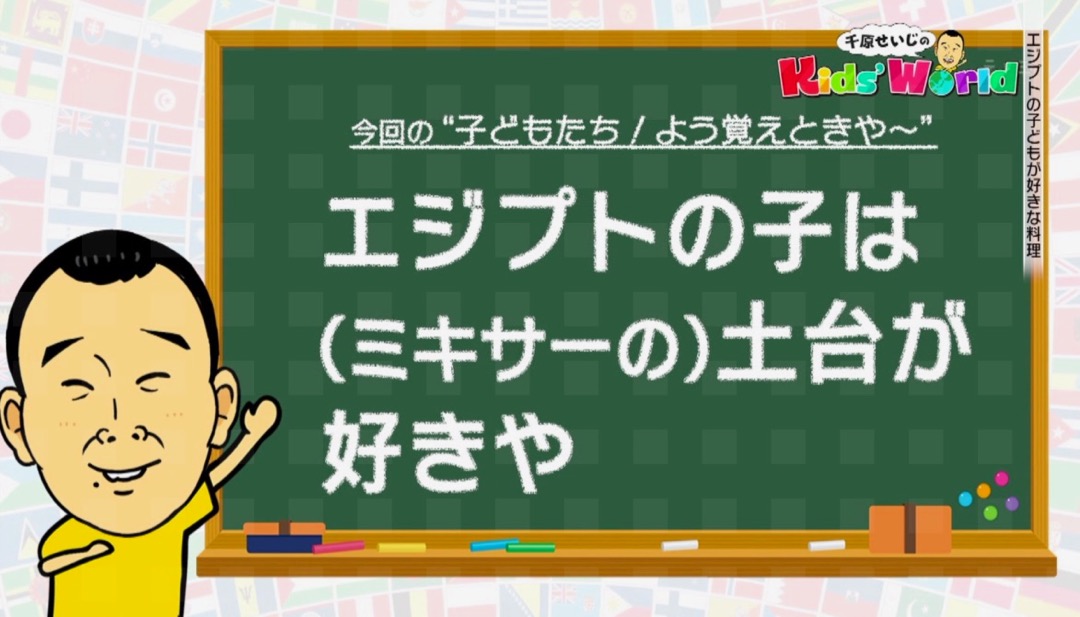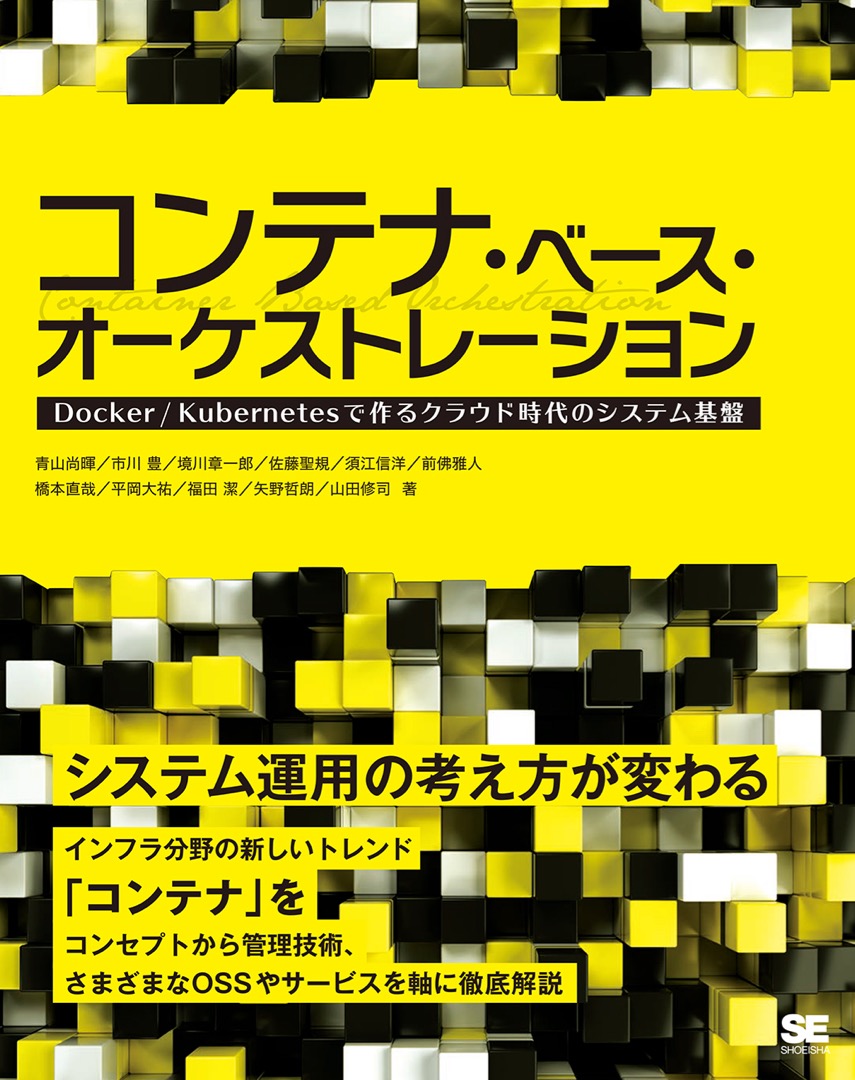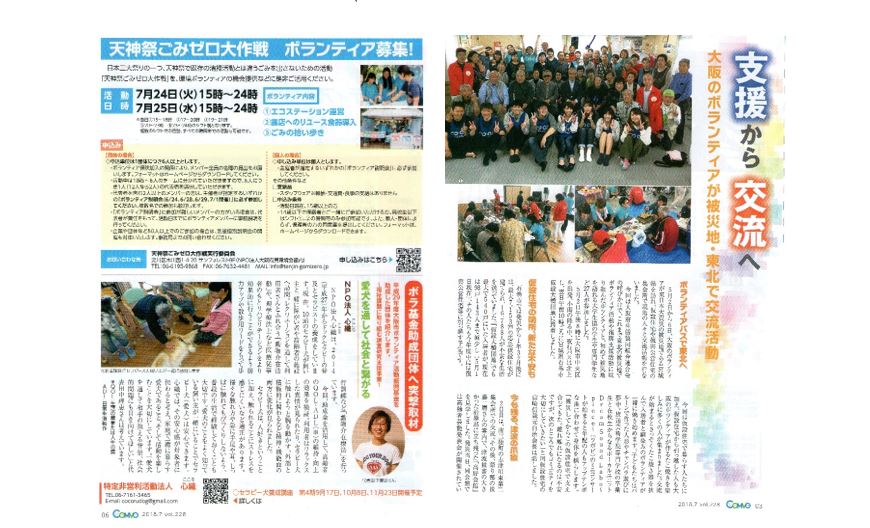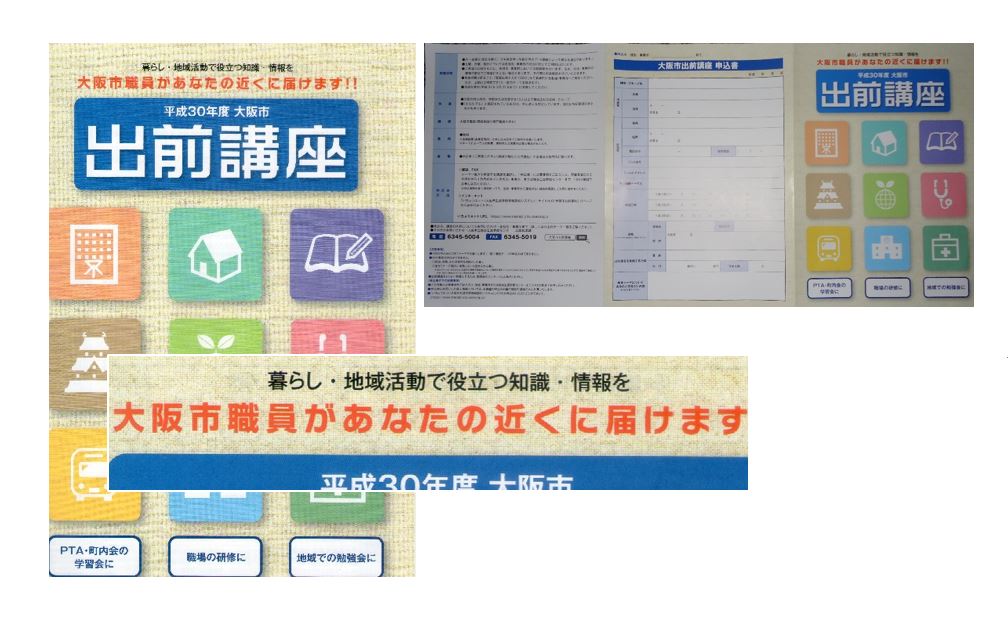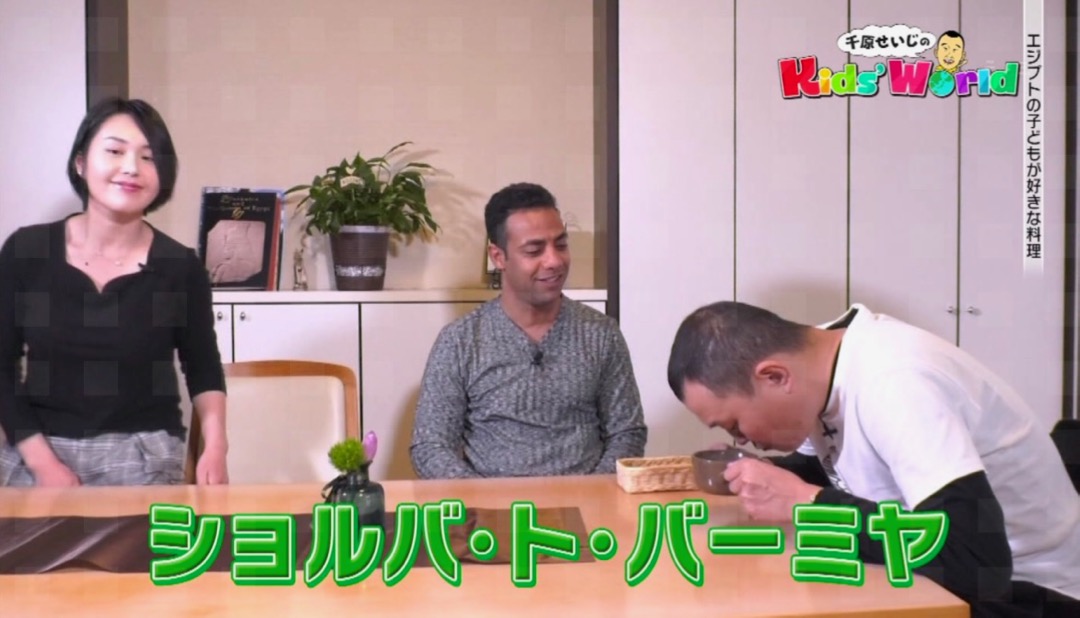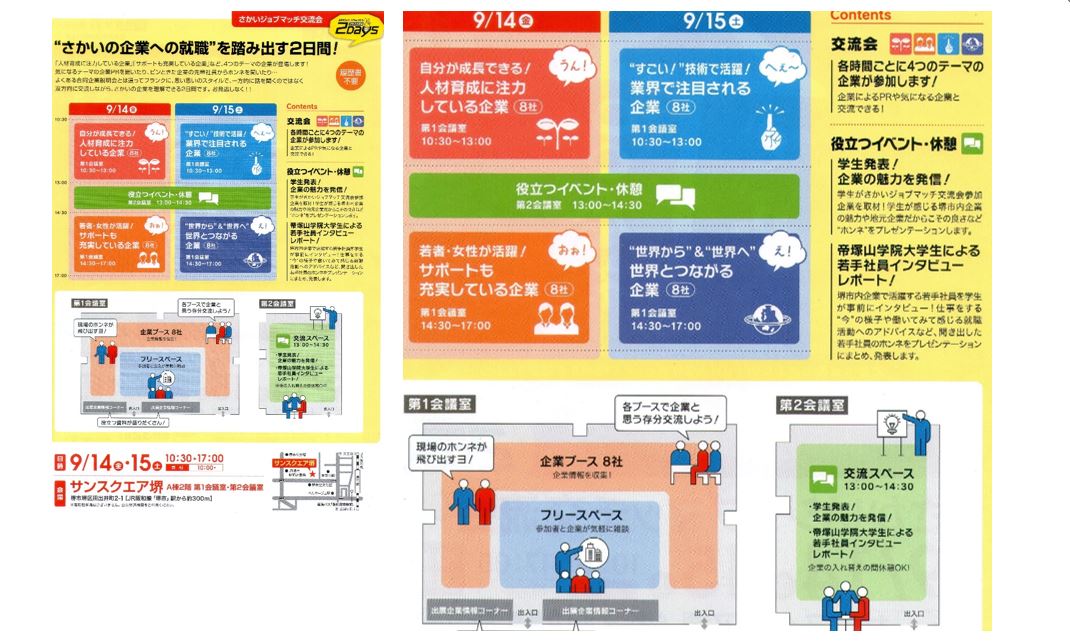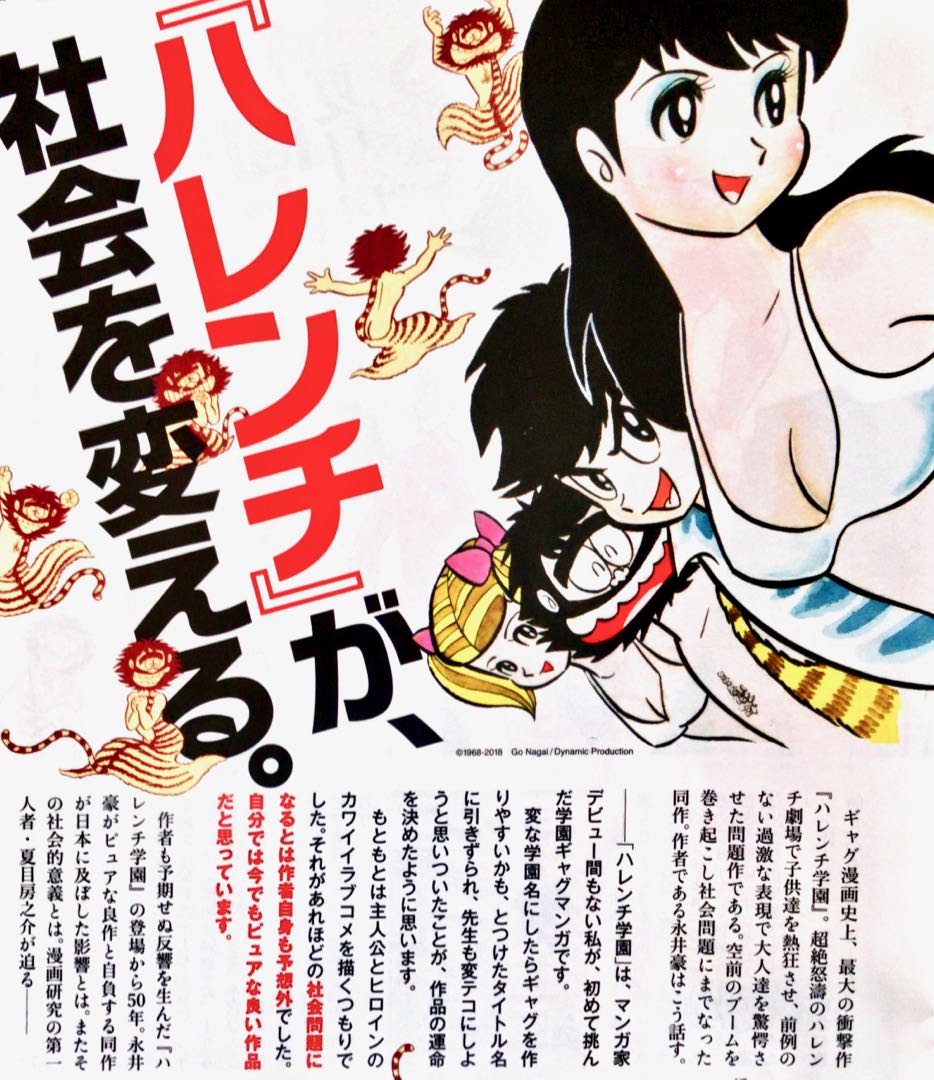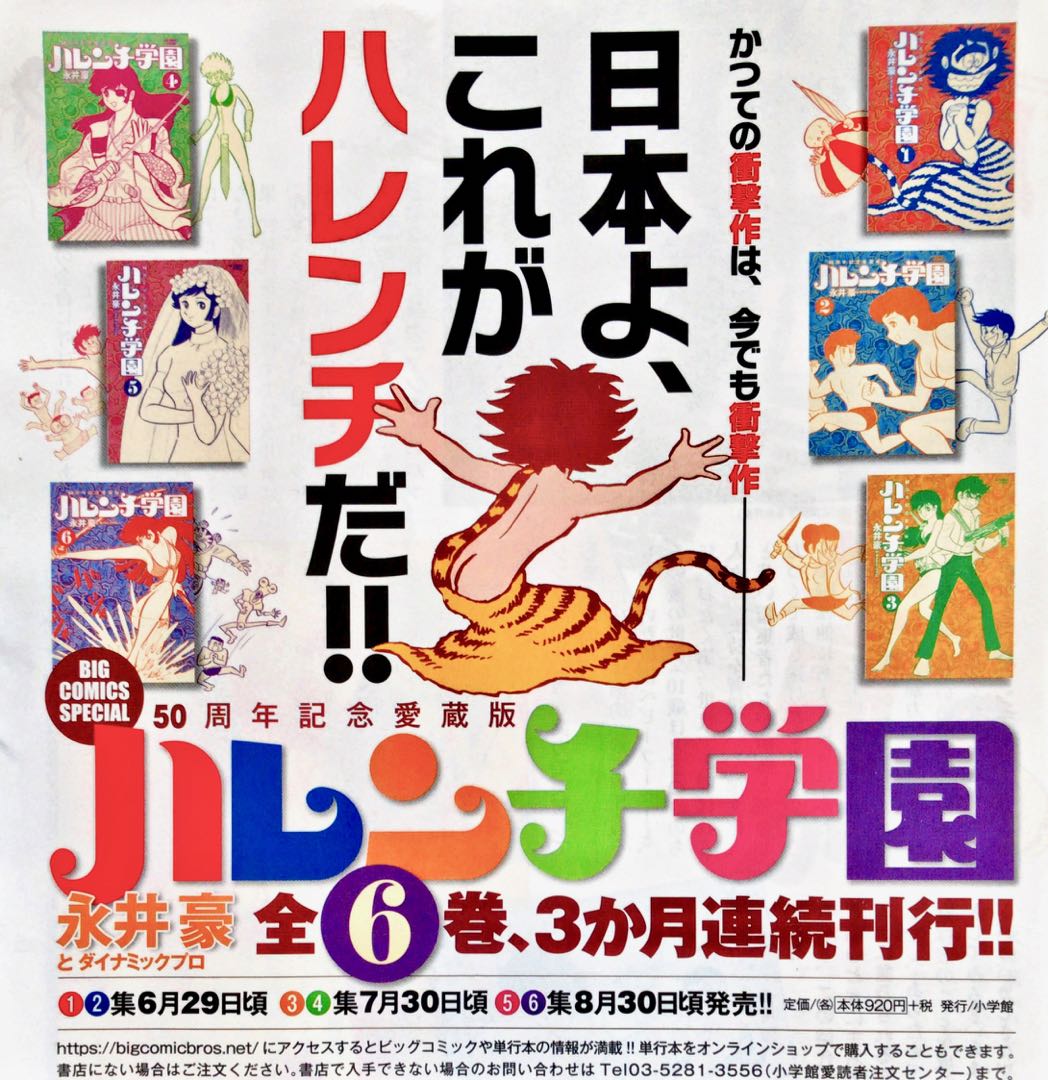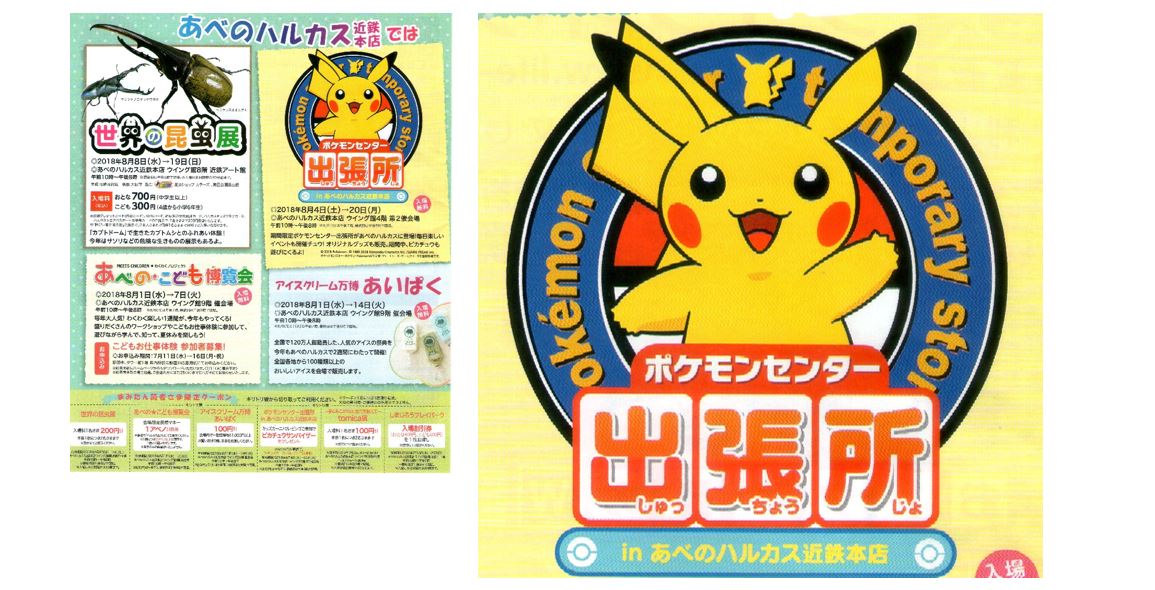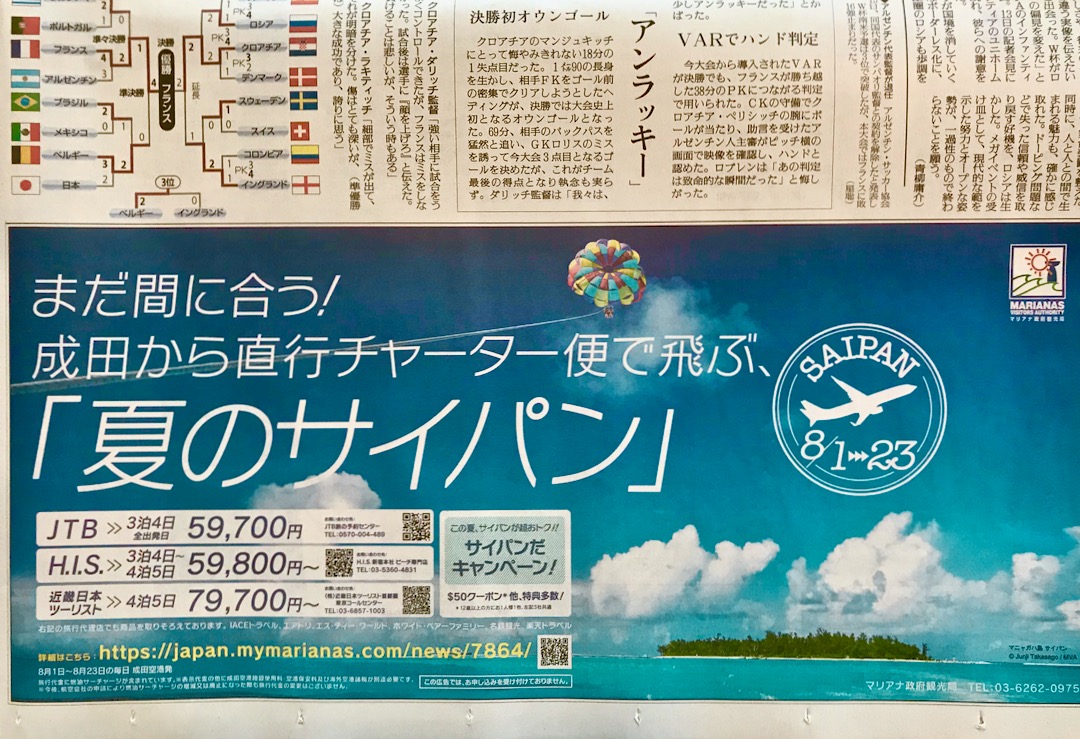
角を丸く処理されています…。
書名:バス・トラック・ダンプカー
著者:元浦年康
発行:学研教育出版
このロゴを使ったポスターは、東武線の駅などに貼られている。
小田急線和泉多摩川の駅前。
縦型の看板にも使われていた。
Nintendo Switchで2018年11月に発売されたゲーム『Let's Go! ピカチュウ』に組み込みでニタラゴ(ロダンNTLG)が使われています。
もう1枚。
こちらはニンテンドー3DS『ポケットモンスター ウルトラサン』(2017年11月発売)より。
最近はゲーム機の画面解像度が上がったことで、アウトラインフォントが使われることがすっかり当たり前のようになりました。
ニンテンドーも、ちょっと前までドットフォントでしたよね。
「トランスフォーマー」シリーズ最新作、バンブルビー。
日本オリジナルTVスポット映像。
書名:ニコリのペンパ(2019)
発行:ニコリ
昨日、日本橋(大阪)まで行く機会があり、そこでニタラゴルイカの使用例を見たので、何枚か上げておきます。
これは、水色の「らしんばん〜」の文字ですね。
これで最後です。
何度も言っていますが、他社に提供されているニタラゴの漢字と違い、数字の「1」とかがとても写真映えしますね〜(笑)。
数字の「1」とかに、気づいてくれる人は少ないですね…。
書名:スクラッチアートミニオンミニ
発行:東京書店
12月7日に発売されたNintendo Switch用ソフト『大乱闘スマッシュブラザーズ SPECIAL』のゲーム内でニタラゴ(ロダンNTLG)が使われているようです。
参考にもう1枚。
購読している新聞のおまけで貰える、Y家庭版という本の付録。
中身ページのタイトルにも多用されていた。